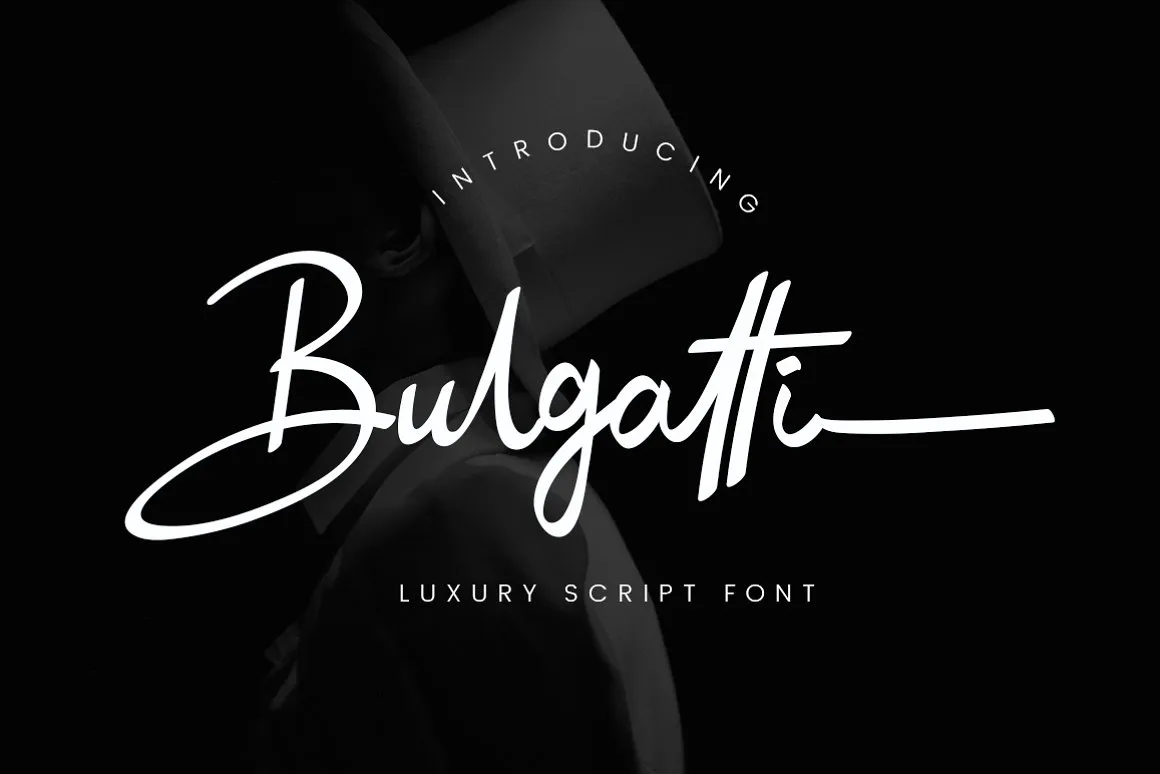
Bulgatti Luxury Script Font – Download Grátis
Estamos muito felizes por você estar olhando para a Bulgatti Luxury Script Font. Esta nova e moderna fonte script é perfeita para quem busca uma opção sofisticada e única para suas criações digitais. Introduzida pela Creatype Studio Co., a Bulgatti oferece um design arrojado que enriquecerá seu próximo projeto, especialmente em áreas como fotografia, marcadores de água, postagens nas redes sociais, anúncios, logomarcas e identidades corporativas, convites, designs de produtos, etiquetas, material de estação ou até mesmo para eventos especiais. Bulgatti é a escolha ideal quando você busca um toque único e elegante que transformará qualquer projeto em algo incrivelmente profissional. Engane-se sobre sua elegância sofisticada e inconfundível – isso certamente trará vida à sua arte digital, seja ela na tela ou impressa. Descubra por si mesmo o fascínio e a beleza da Bulgatti Luxury Script Font.